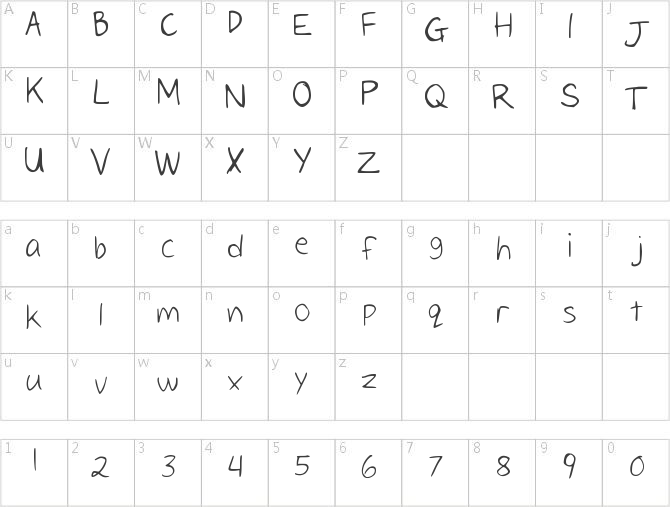
IceCream-Medium 詳情頁
字體名稱: IceCrea
IceCream-Medium
IceCream-Medium介紹
IceCream-Medium字體字庫是一款讓人賞心悅目、百看不厭的英文字體,適合各類廣告和產品包裝設計應用,字體大小0.02MB,格式為ttf字體,上傳用戶是志誠設計,作者/版權方為未知